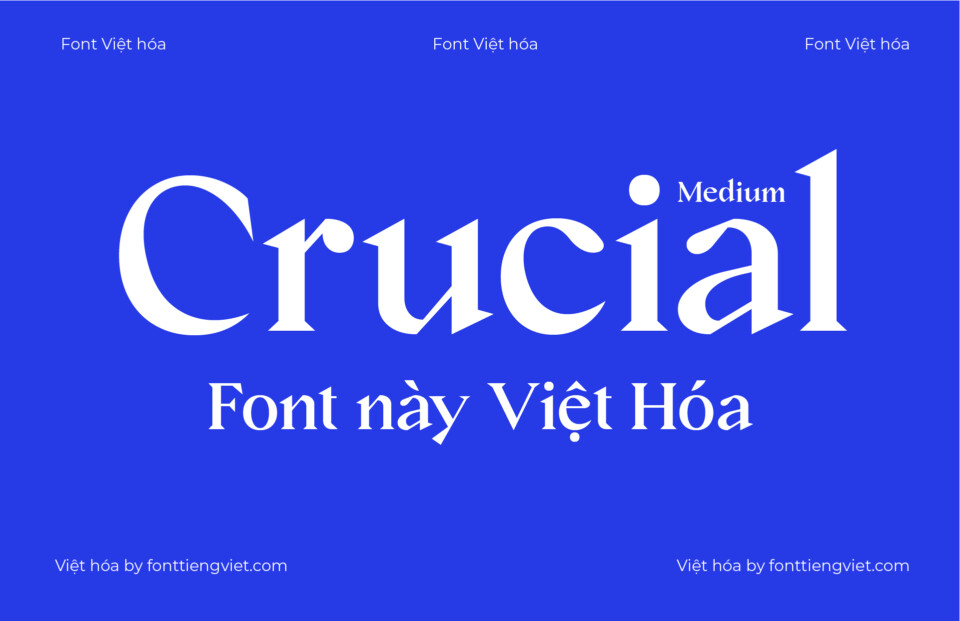
Font Việt hóa 1FTV Crucial Medium ( 2 file )
Giới thiệu về Font Việt hóa 1FTV Crucial Medium ( 2 file )
Trong thế giới thiết kế đồ họa hiện đại, việc lựa chọn một Font Miễn Phí chất lượng luôn là ưu tiên hàng đầu của các bạn học sinh và thầy cô giáo. Font Việt hóa 1FTV Crucial Medium ( 2 file ) là một bộ phông chữ mang phong cách tối giản nhưng vô cùng mạnh mẽ. Với đường nét rõ ràng và độ dày vừa phải, bộ font này giúp các văn bản học thuật hay bài thuyết trình trở nên chuyên nghiệp hơn bao giờ hết. Việc sở hữu đầy đủ 2 file định dạng giúp người dùng linh hoạt cài đặt trên nhiều thiết bị khác nhau từ máy tính đến điện thoại.
Đặc điểm nổi bật của bộ font
Bộ Font Việt hóa 1FTV Crucial Medium ( 2 file ) nổi bật nhờ sự cân bằng giữa tính thẩm mỹ và khả năng đọc hiểu. Các ký tự tiếng Việt được tinh chỉnh kỹ lưỡng, đảm bảo không lỗi dấu khi soạn thảo trên Word hay Canva. Đây là lựa chọn lý tưởng cho các bạn muốn tạo ra những tiêu đề bài giảng sinh động hoặc làm nổi bật các ý chính trong báo cáo khoa học. Cấu trúc hình học của font tạo cảm giác hiện đại, trẻ trung, rất phù hợp với xu hướng sáng tạo nội dung của thế hệ Gen Z hiện nay.
Cách sử dụng Font Việt hóa 1FTV Crucial Medium ( 2 file ) hiệu quả
Kết luận về bộ phông chữ chuyên dụng